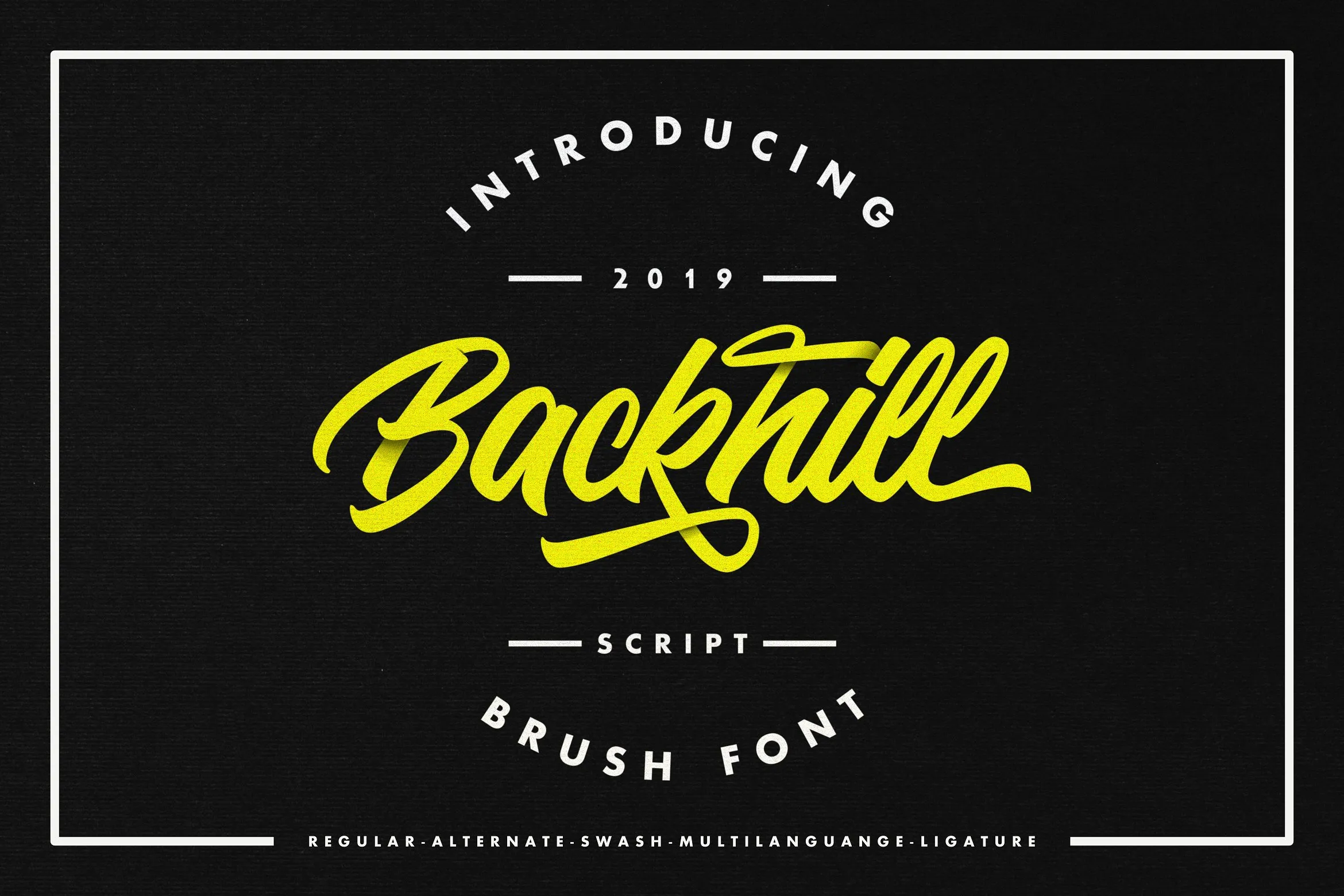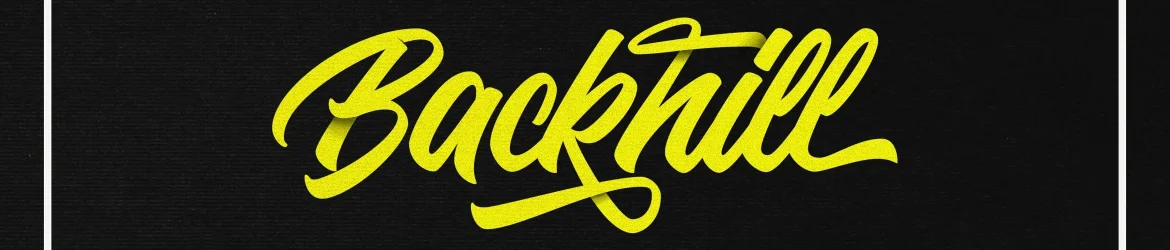
Backhill Bold Script Font – Download Grátis
Agradecemos pela oportunidade de apresentar esta bela fonte chamada Backhill Bold Script Font. Esta família de caracteres script foi cuidadosamente criada para manter cada detalhe, desde os mais sutis até as mais aparentes. Inspirado na arte dos desenhos a mão e revestido com opções variadas como alternativas de tipo aberto, ligaturas comuns e variações swash, o Backhill Bold Script Font é uma escolha excepcional para trabalhos que precisam do toque natural das letras à mão. Este design foi criado por Inspiratype e elaborado pelo designer Hamilton. Ideal tanto para logotipos quanto para cartões de visita, rótulos ou até mesmo desenhos a gráfico em camisetas, esta fonte oferece uma gama única de personalização que certamente irá transformar qualquer projeto em algo autêntico e único. E com sua aparência clara e levemente distorcida, ela cria um equilíbrio perfeito entre modernidade e estética artesanal. Através do Backhill Bold Script Font, você pode explorar uma nova forma de expressão visual em seus projetos.